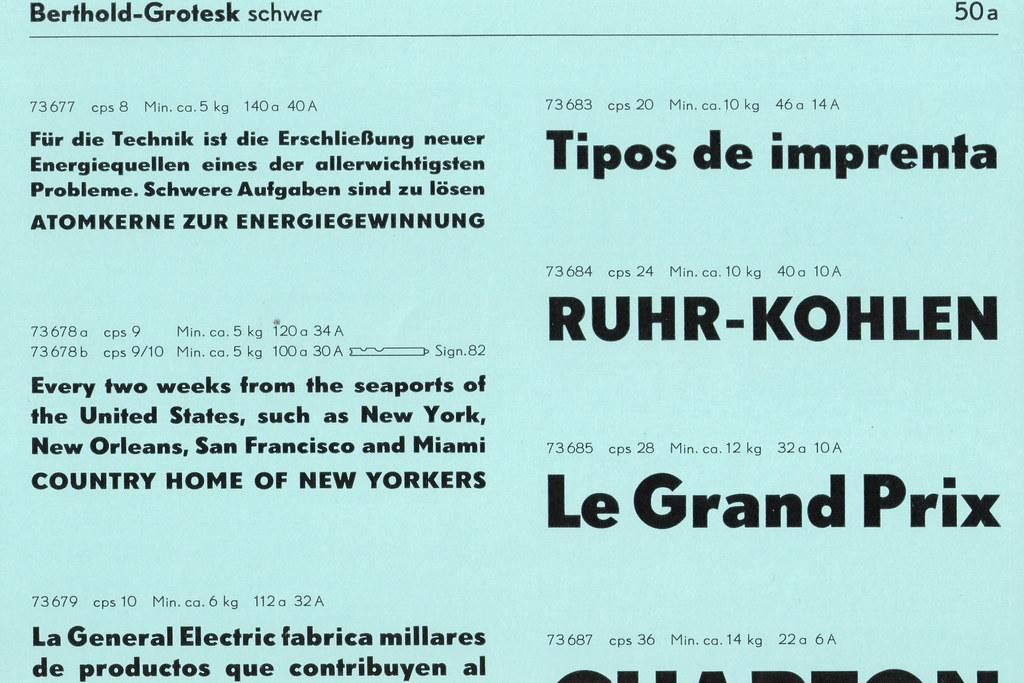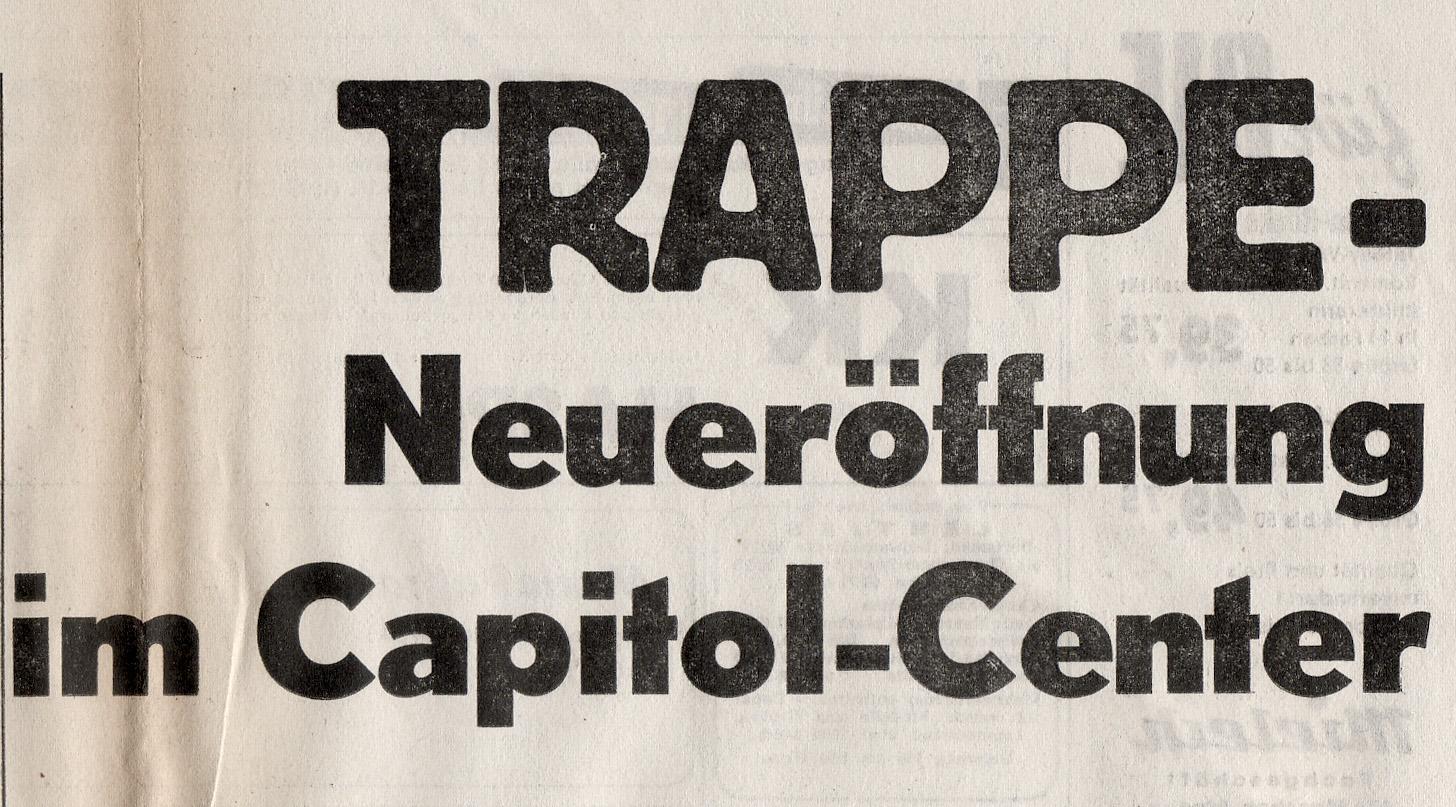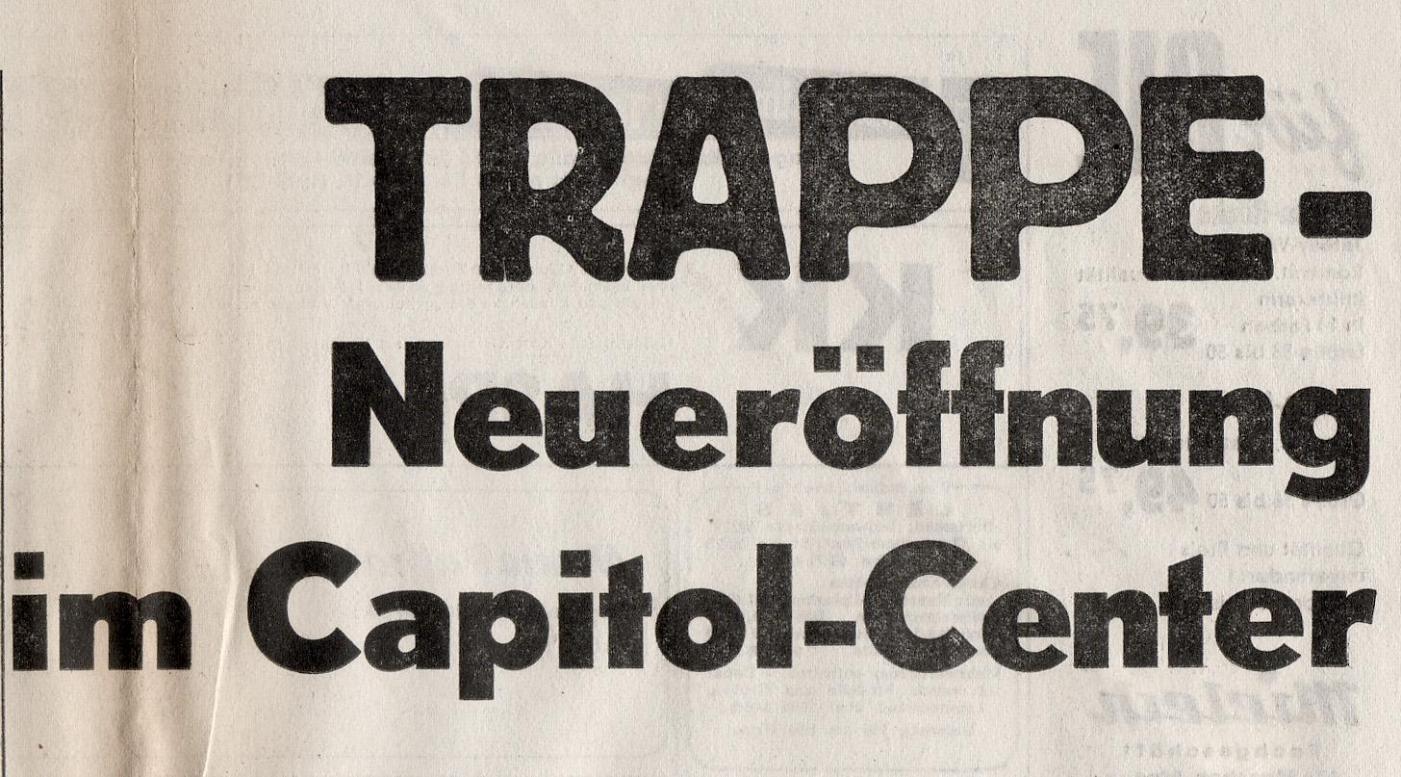
Type "Erbar-Grotesk", aber anders
Immer wieder kommt mir bei Durchsicht alter Zeitungsannoncen aus den 60er und 70er Jahren
eine Alternativ-Form der "Erbar-Grotesk" zu Gesicht.
Welche Schrift ist es wirklich?
2. u. 3. Zeile ("... Neueröffnung im Capitol-Center")